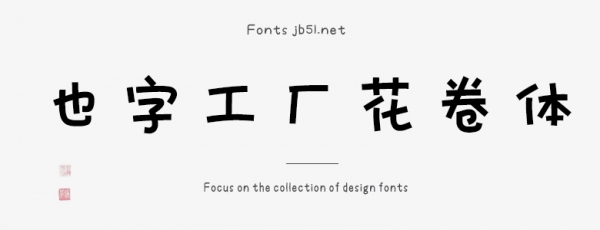
也字工廠花卷體是由也字工廠出品的藝術(shù)字體,字體筆觸適中,字形圓潤(rùn)略顯可愛(ài),具有很好的視覺(jué)感,適合應(yīng)用于藝術(shù)設(shè)計(jì)、平面宣傳設(shè)計(jì)、網(wǎng)頁(yè)設(shè)計(jì),書(shū)法字帖等領(lǐng)域,需要的朋友可以前來(lái)本站下載。